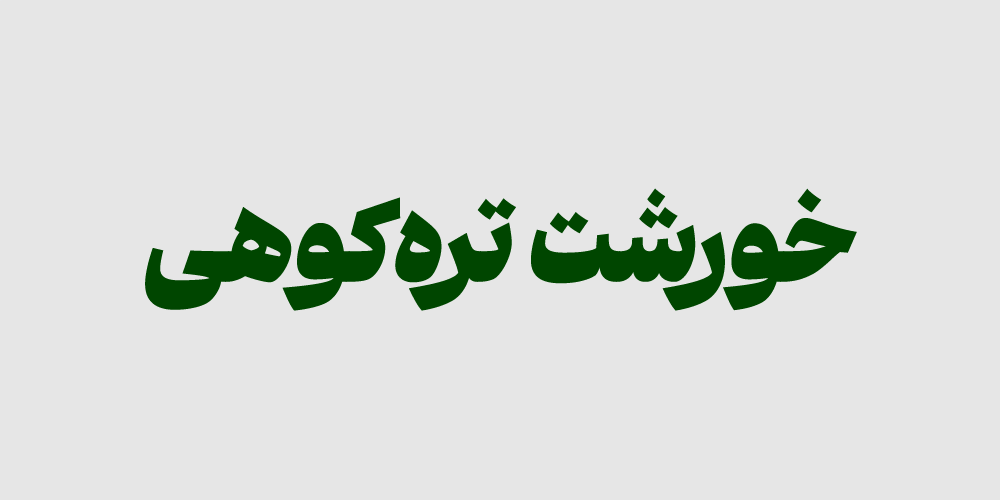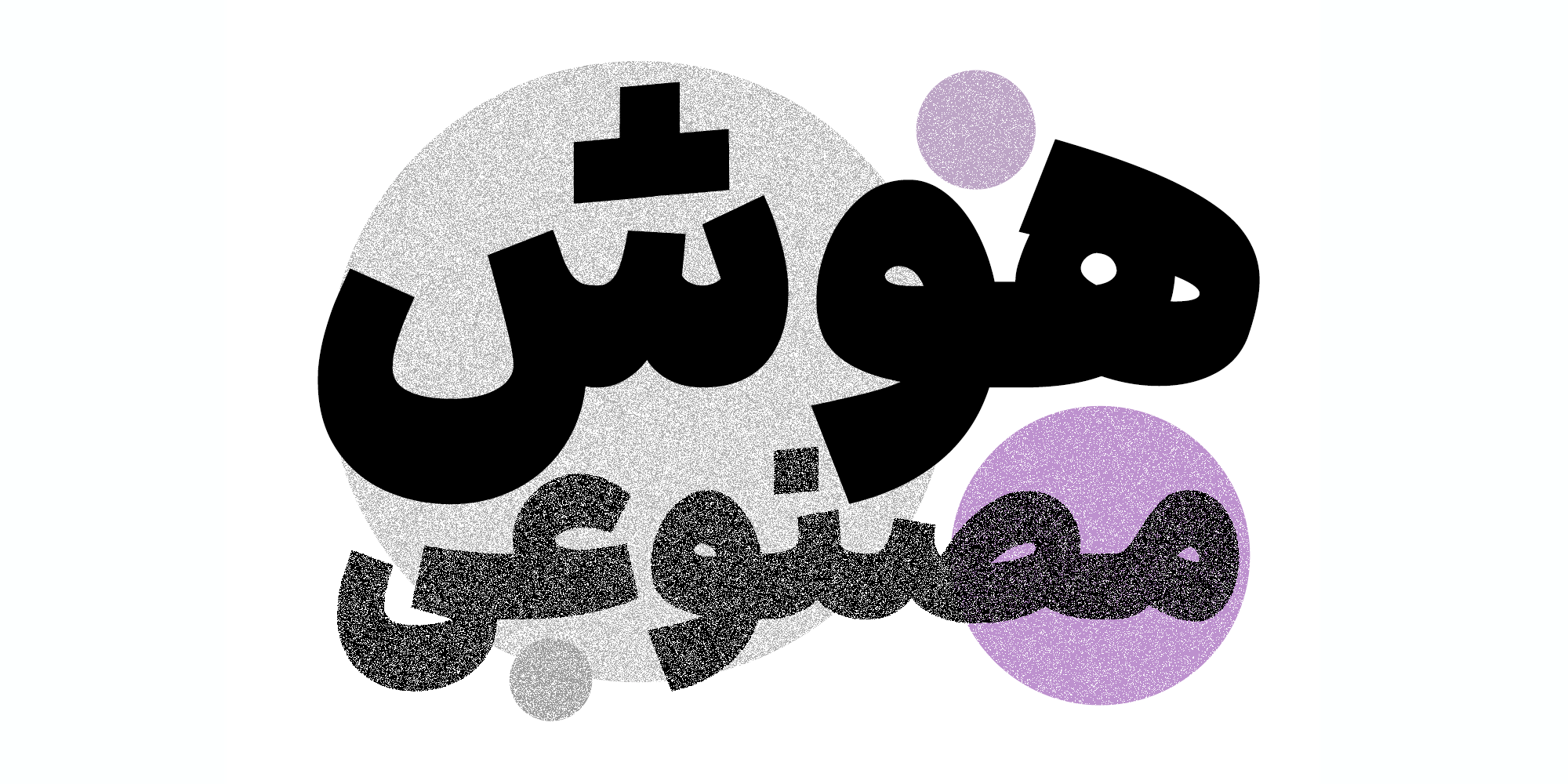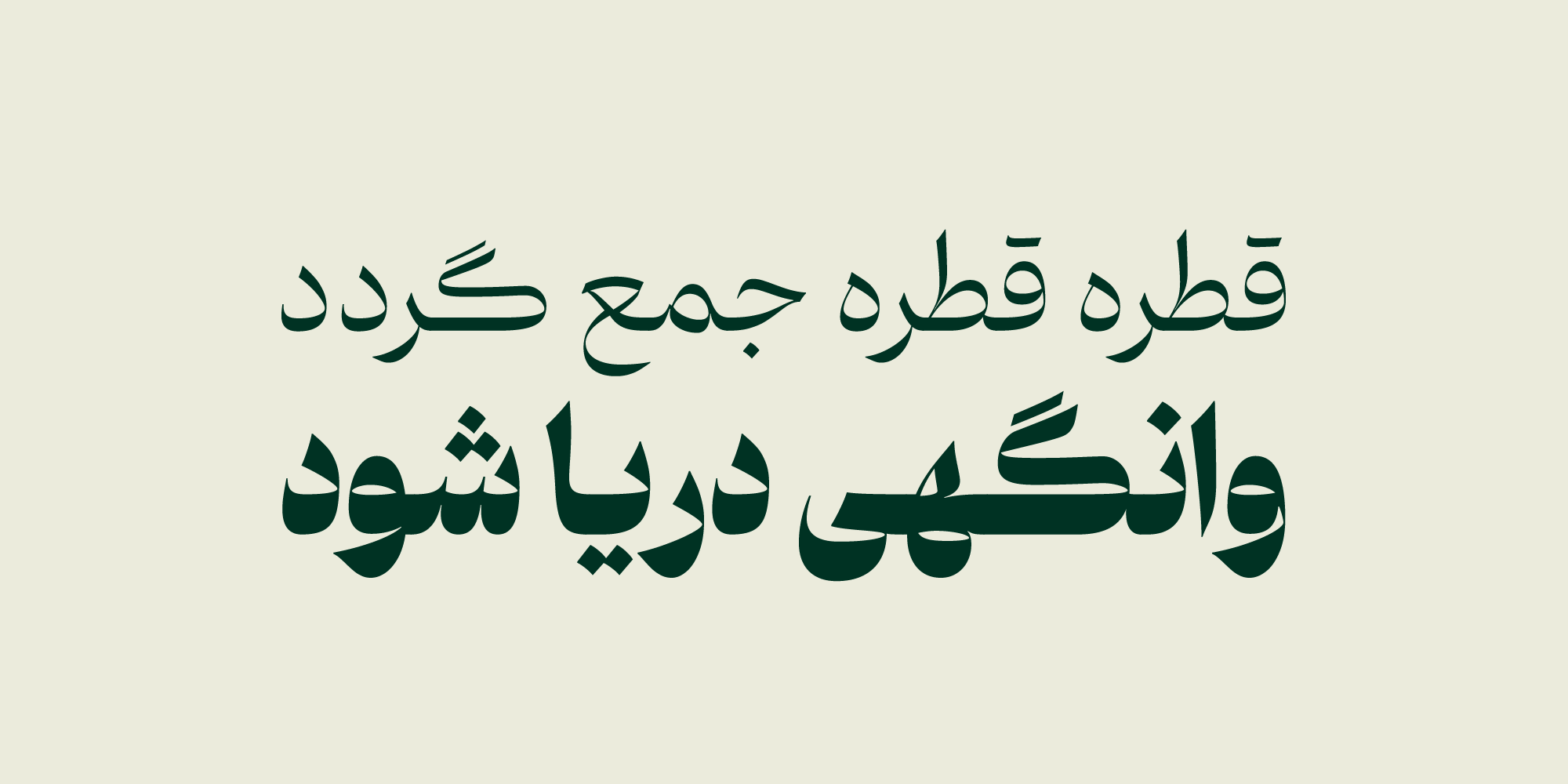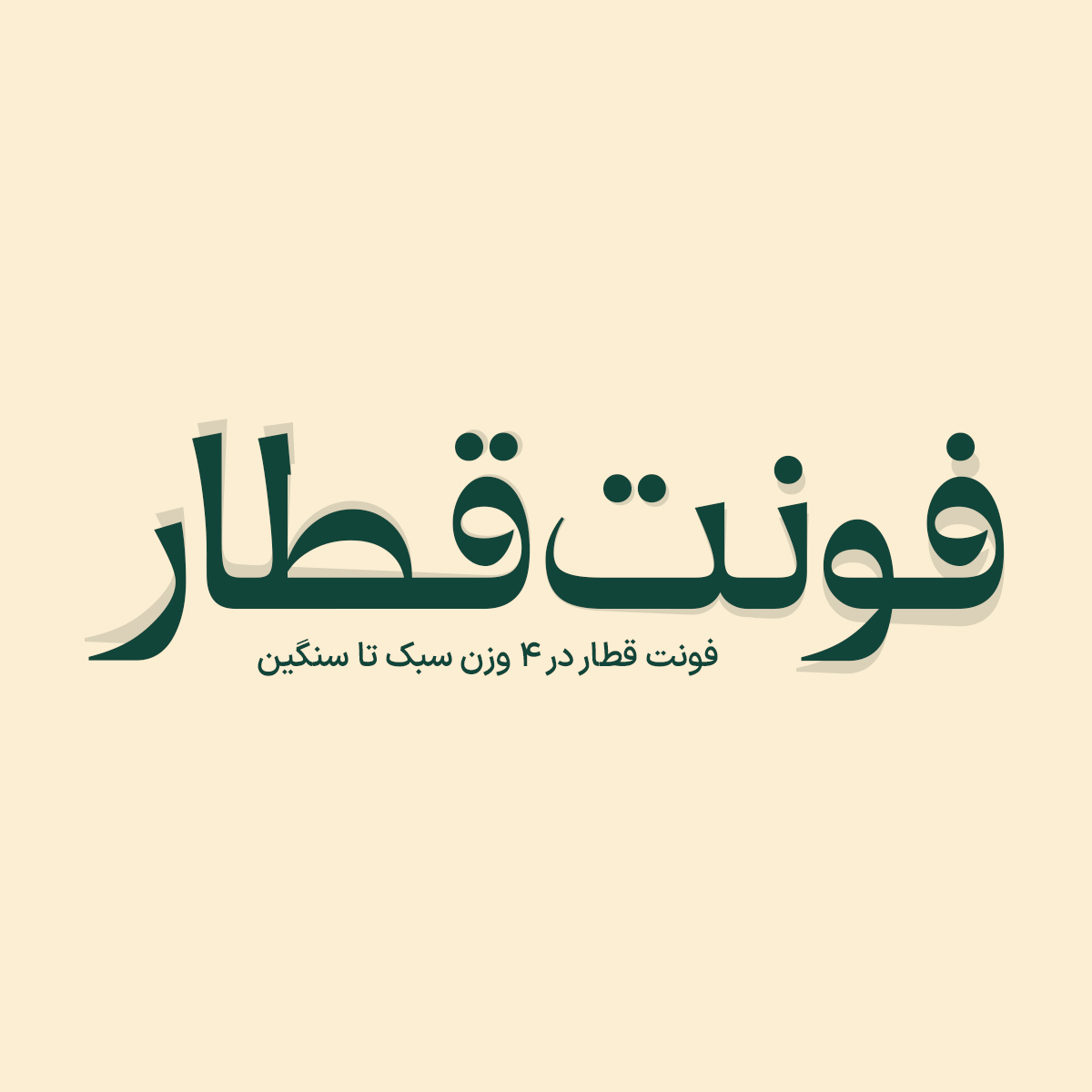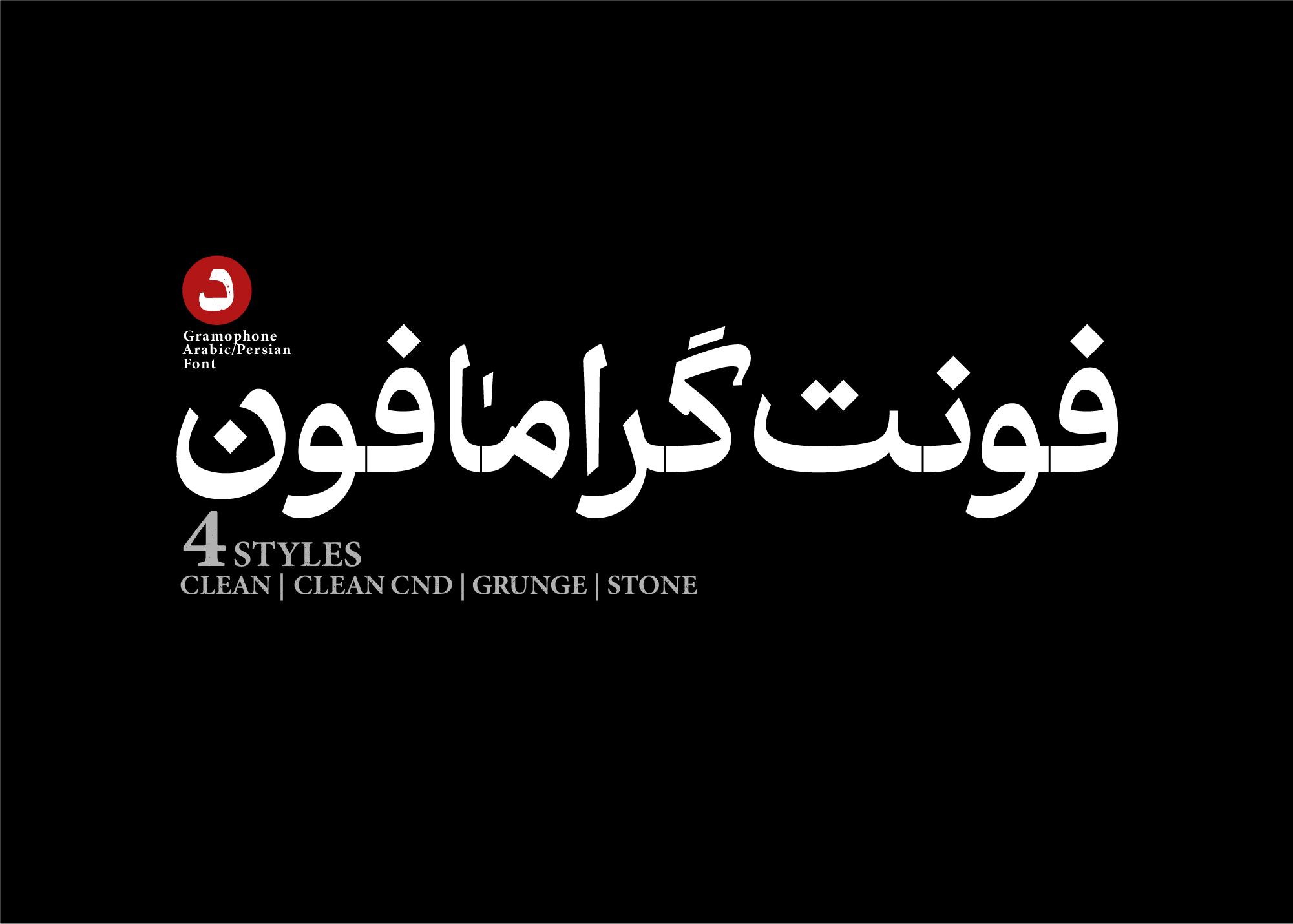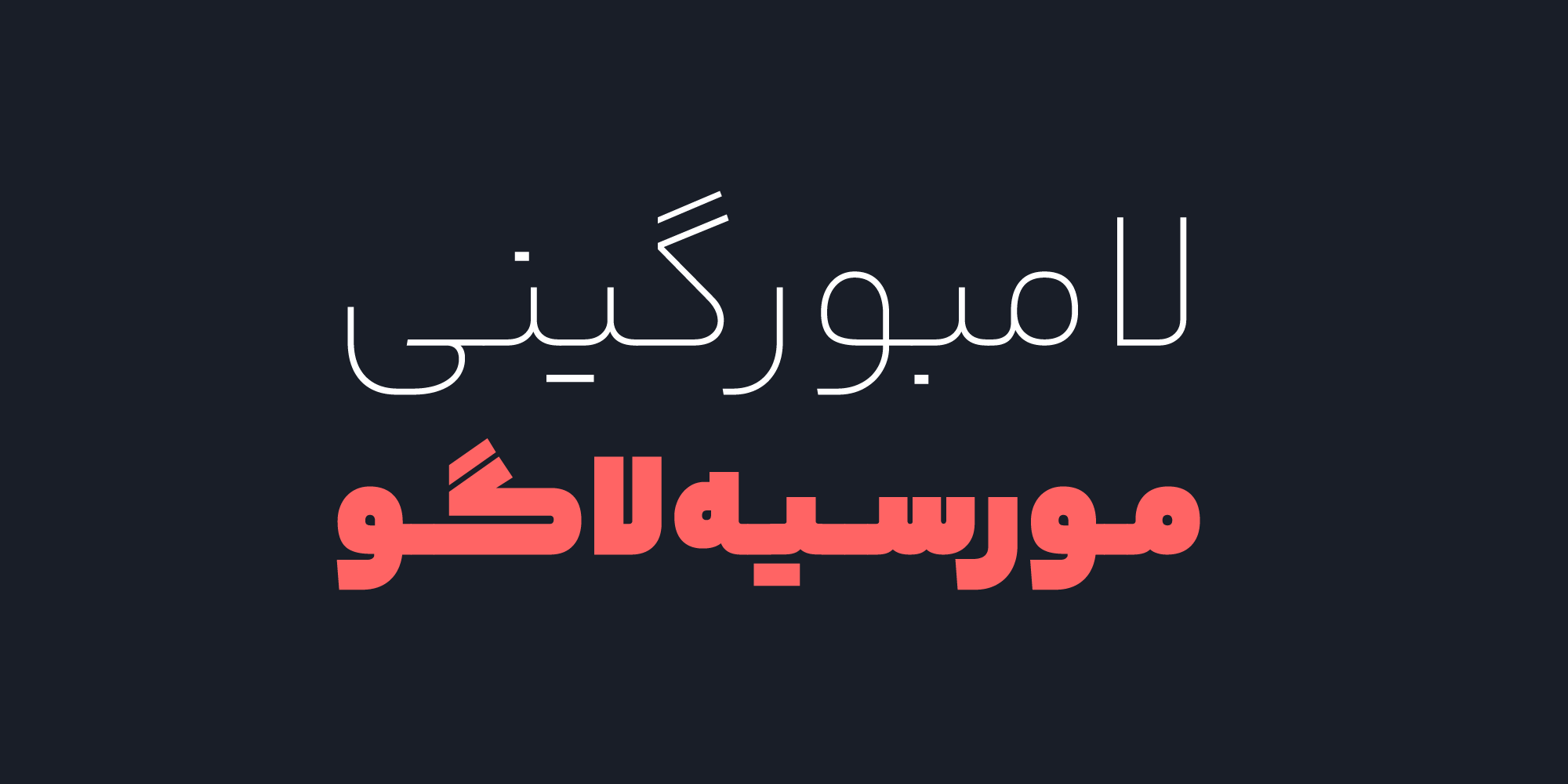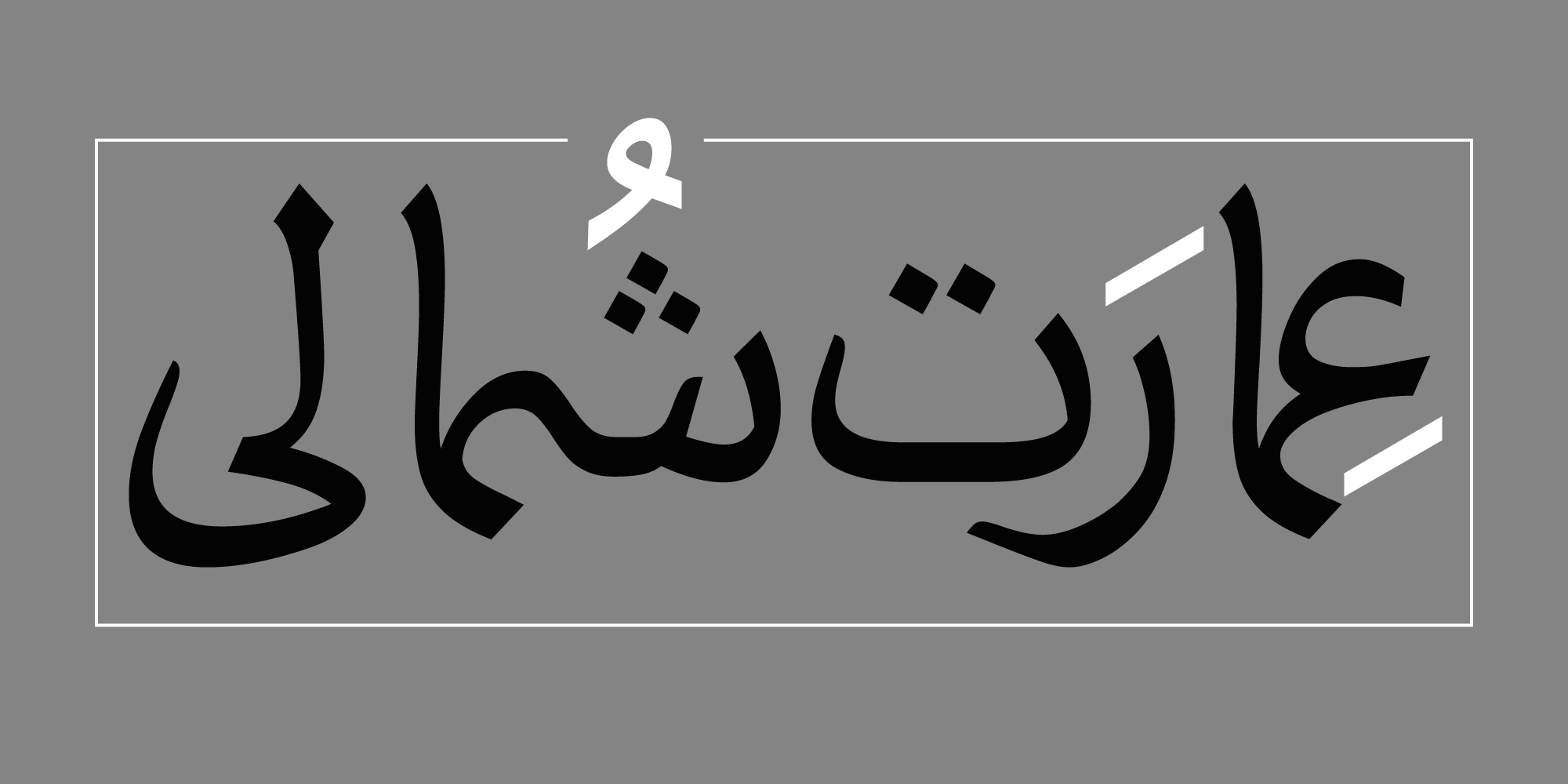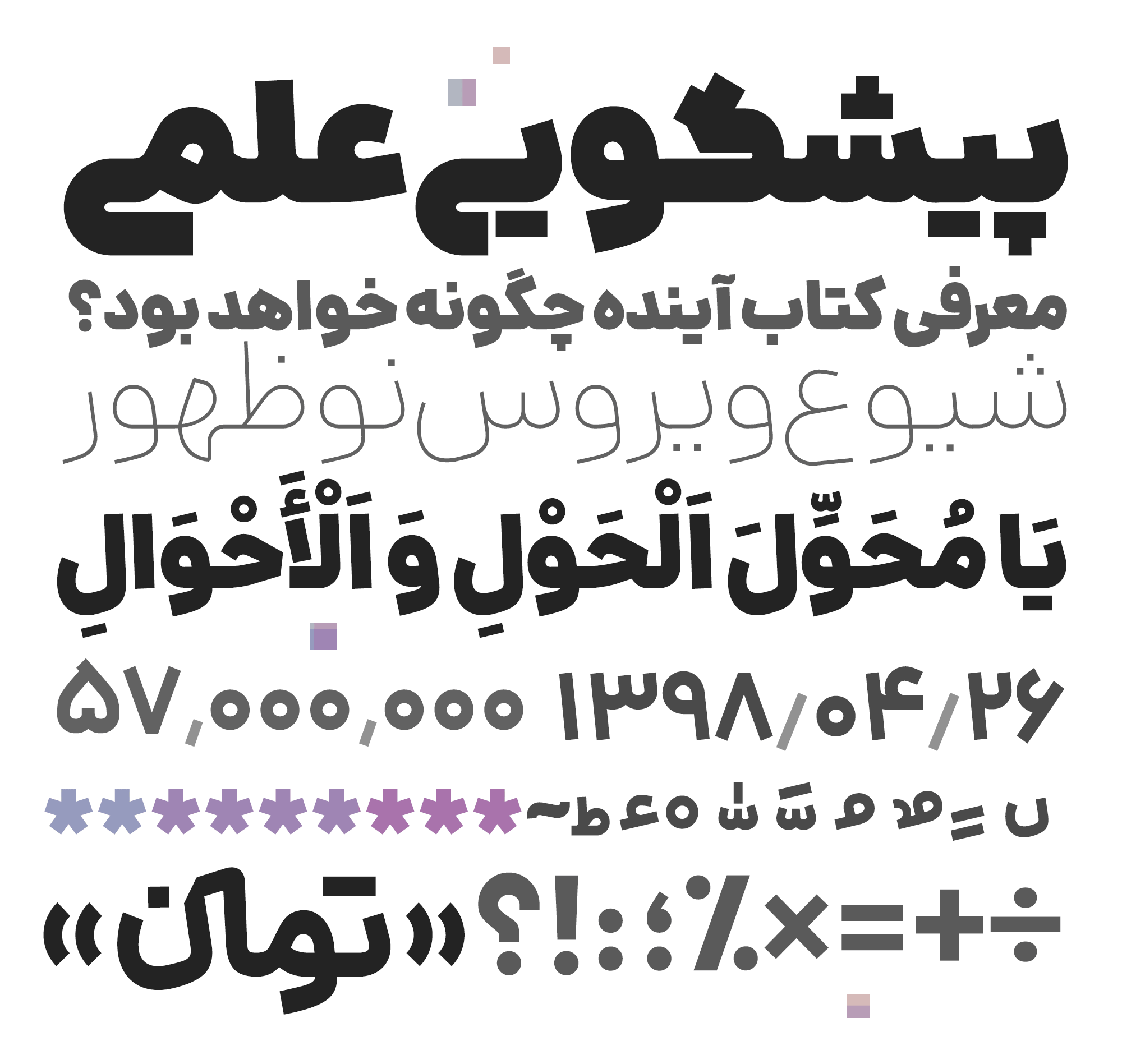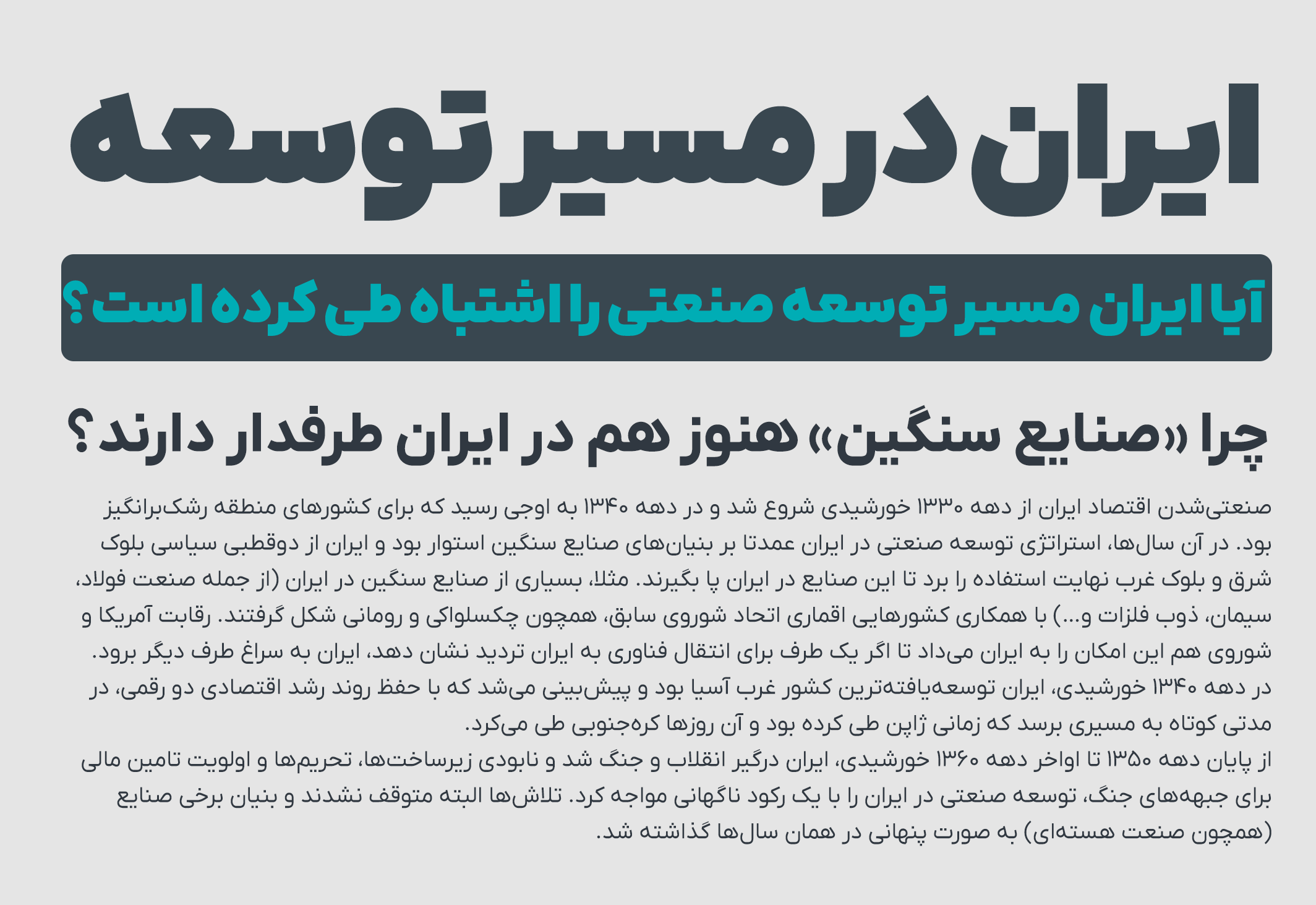
جلد یک کتاب، ویترین دنیاییست که درون آن پنهان شده. درست مثل یک نگاه اول، تأثیرگذار، عاطفی و ماندگار. در طراحی جلد کتابهای فارسی، انتخاب فونت مناسب چیزی فراتر از یک تصمیم گرافیکی ساده است؛ این انتخاب میتواند لحن کتاب را روایت کند، مخاطب را به خود جذب کند و حتی هویت برند نویسنده یا ناشر را بسازد. اگر به دنبال بهترین فونت فارسی برای جلد کتاب خود هستید، در جای درستی قرار دارید.
در این مقاله از سایت دیاکوگرافیک، با معرفی مجموعهای از بهترین فونتهای فارسی مخصوص جلد کتاب که توسط حرفهایترین طراحان گرافیک ایران استفاده میشود، به شما کمک میکنیم تا انتخابی حرفهای، زیبا و تاثیرگذار داشته باشید. هدف ما ارائه اطلاعاتی کامل برای انتخاب بهترین فونت فارسی برای جلد کتاب است که هم از نظر زیباییشناسی و هم کاربرد حرفهای، بینقص باشد.
چرا انتخاب فونت برای جلد کتاب اهمیت دارد؟
فونت فقط یک ابزار بصری نیست؛ بلکه بخشی از روایت و احساس کتاب شماست. یک فونت مناسب میتواند:
- حال و هوای کتاب را در نگاه اول منتقل کند؛
- تمایز بصری کتاب شما در قفسه کتابفروشی را افزایش دهد؛
- حس اعتماد، تخصص یا خلاقیت را القا کند؛
- در ذهن مخاطب ماندگار شود.
بنابراین اگر به طراحی جلد حرفهای فکر میکنید، نباید از کنار فونت بهسادگی عبور کنید. استفاده از بهترین فونت فارسی برای جلد کتاب، برگ برندهای در بازاریابی بصری و جذب نگاه مخاطب است. این انتخاب میتواند تأثیر مستقیمی در تصمیم خرید مخاطب داشته باشد، چرا که اولین چیزی که دیده میشود، طراحی جلد و فونت تیتر آن است.
معرفی بهترین فونتهای فارسی برای جلد کتاب
در ادامه با ۱۰ فونت حرفهای، زیبا و امتحانپسداده آشنا میشویم که هرکدام ویژگیها و حسوحال خاص خود را دارند. انتخاب این فونتها بر اساس کاربرد در پروژههای واقعی، محبوبیت میان طراحان و هماهنگی با انواع سبکهای محتوایی انجام شده است. این فهرست با تمرکز بر معرفی بهترین فونت فارسی برای جلد کتاب گردآوری شده است.
۱. فونت گرامافون
گرامافون ترکیبی بینظیر از نوستالژی و مدرنیته است. طراحی این فونت الهامگرفته از تابلوهای قدیمی، تایپوگرافی سنتی ایرانی و زیباییشناسی کلاسیک است. ویژگی بارز این فونت، حرکت نرم در فرم حروف و منحنیهای دلنشین آن است که آن را برای جلد کتابهایی با حالوهوای ادبی، عاشقانه یا تاریخی بیرقیب میکند. اگر به دنبال بهترین فونت فارسی برای جلد کتابهای کلاسیک هستید، گرامافون یک انتخاب هوشمندانه است.
۲. فونت قطار
قطار فونتی مدرن و ساختارشکن است که با رویکردی نوآورانه طراحی شده. این فونت دارای ساختاری دینامیک و پرانرژی است که خطوط ضخیم و گرافیکی آن، حس حرکت و پویایی را به جلد منتقل میکند. اگر قصد دارید جلد کتاب شما متمایز، مدرن و پرانرژی باشد، قطار گزینهای ایدهآل است.
در دستهبندی بهترین فونت فارسی برای جلد کتابهایی با فضای معاصر و آیندهنگر، فونت قطار جایگاه ویژهای دارد.
۳. فونت ابر
فونت ابر انتخابی بینقص برای طراحیهای خلوت، شاعرانه و آرام است. حروف نرم، خوانا و سبک آن، فضایی شاعرانه و آرامشبخش به جلد میدهد. این فونت برای کتابهای شعر نو، ادبیات لطیف، یا حتی آثار روانشناسی و معنوی مناسب است.
اگر میخواهید بهترین فونت فارسی برای جلد کتاب شعر را انتخاب کنید، ابر گزینهای ایدهآل است.
۴. فونت دانا
دانا یک فونت سازمانی و چندمنظوره است که با حفظ خوانایی بالا، ظاهری متین و منظم دارد. این ویژگیها باعث میشود برای جلد کتابهایی با محتوای رسمی، آموزشی یا علمی بسیار مناسب باشد.
اگر به دنبال بهترین فونت فارسی برای جلد کتابهای دانشگاهی یا پژوهشی هستید، دانا میتواند انتخابی بینقص باشد.
۵. فونت ایرانسنس
ایرانسنس یکی از پرکاربردترین فونتهای فارسی در سالهای اخیر بوده است. این فونت با ظاهر مدرن و خوانا، برای جلد کتابهایی که قرار است حس پویایی، روزآمد بودن یا تکنولوژی را منتقل کنند بسیار مناسب است.
این فونت در فهرست بهترین فونت فارسی برای جلد کتابهایی با موضوع دیجیتال یا مدرن، جایگاه ویژهای دارد.
۶. فونت ایرانیکان
ایرانیکان با ساختار منحنی و روان، یکی از دوستداشتنیترین فونتها برای طراحی جلد کتابهای عمومی است. این فونت حسی از مهربانی، سادگی و دسترسی را منتقل میکند و مناسب کتابهای داستان، روانشناسی عمومی، کودک و نوجوان است.
در طراحی بهترین فونت فارسی برای جلد کتابهای سبک خودیاری و اجتماعی، ایرانیکان درخششی خاص دارد.
۷. فونت دوران
فونت دوران الهامگرفته از طراحی سنتی با نگاهی مدرن است. ساختار آن اصیل، متوازن و بسیار مناسب برای کتابهاییست که رنگ و بوی فرهنگ ایرانی، ادبیات کلاسیک یا روایتهای تاریخی دارند.
اگر جلد کتاب شما باید حس اصالت ایرانی را منتقل کند، دوران بدون شک یکی از بهترین فونتهای فارسی برای جلد کتاب خواهد بود.
۸. فونت یکانبخ
یکان بخ بازطراحی خلاقانهای از فونت محبوب یکان است. این فونت استایل مدرنتر، ساختار منظمتر و وزنهای متنوعتری دارد که آن را به انتخابی عالی برای جلد کتابهای مرتبط با تکنولوژی، استارتاپها، علوم جدید و حتی طراحی تبدیل کرده است.
برای طراحی بهترین فونت فارسی برای جلد کتابهایی که آیندهنگر هستند، یکانبخ یک انتخاب ممتاز است.
۹. فونت دامون
دامون فونتیست هنری، غیرمعمول و خاص. طراحی آن به گونهای است که به جلد کتاب یک هویت هنری و متفاوت میبخشد. این فونت برای کتابهای گرافیکی، نمایشگاهها، موضوعات بصری یا کتابهایی با رویکرد تجربی بسیار مناسب است.
برای طراحی هنریترین و بهترین فونت فارسی برای جلد کتابهای بصری، دامون درخشش خاصی دارد.
پاسخ: فونتهایی مثل ابر و گرامافون به دلیل ساختار لطیف و حس شاعرانه، برای کتابهای شعر بسیار مناسباند و میتوان آنها را بهترین فونت فارسی برای جلد کتاب شعر دانست.
فونت مناسب برای جلد کتاب کودک چیست؟
پاسخ: فونتهایی مانند ایرانیکان و نارنج با حالوهوای دوستانه و نرم، برای کتابهای کودک انتخابهای خوبی هستند.
چطور فونت مناسب را انتخاب کنیم؟
پاسخ: به لحن کتاب، گروه سنی مخاطب، موضوع اثر و حس کلی که میخواهید منتقل کنید دقت کنید. فونت باید در خدمت داستان شما باشد. همچنین توجه به لیست بهترین فونت فارسی برای جلد کتاب میتواند انتخاب شما را سریعتر و حرفهایتر کند.